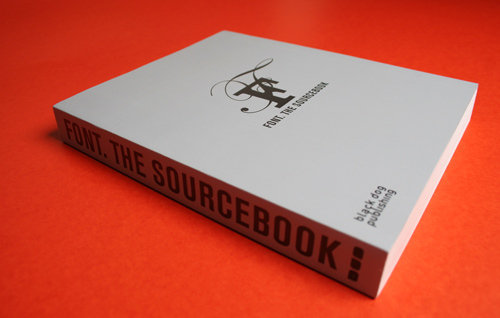
»Font. The Sourcebook« beschäftigt sich mit der Geschichte der Schrift als Kommunikations-, Design-, Darstellungs- und Kunst-Element. So erfährt man ein paar Fakten zu bekannten Schriften oder frischt vorhandenes Wissen einfach auf.
Über 50 Schriften, die die Geschichte am Meisten beeinflusst haben, werden jeweils auf einer Doppelseite behandelt. Darunter die: Akzidenz Grotesk, Baskerville, Caslon, DIN, Frutiger, Garamond, Helvetiva, Interstate, Joanna, Knockout, Lucida, Matrix, News Gothic, Officina, Perpetua, Quadraat, Rockwell, Syntax, Times New Roman, Univers, Walbaum, Zapfina.
Zudem enthalten sind Kommentare und Essays von wichtigen Designern, Kritikern und Typografen unserer Zeit wie beispielsweise David Pearson, Ed Fella, Peter Bil’ak oder Sam Winston.
Das Buch ist eine wertvolle und inspirierende Quelle für jeden Designer und dient sicher auch als Hilfsmittel bei der Auswahl von Schriften.
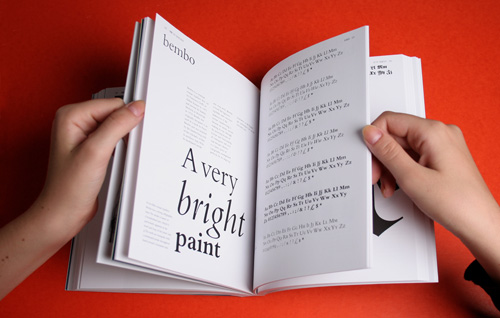
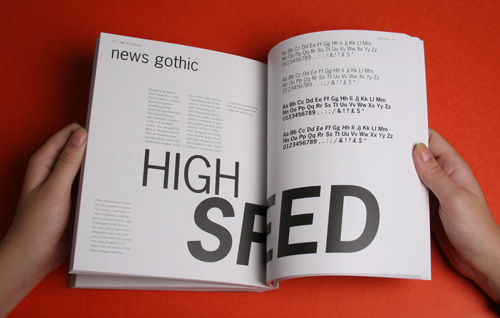
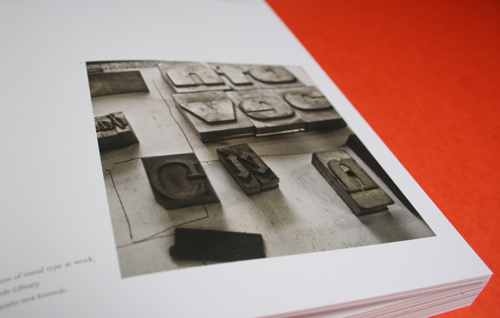
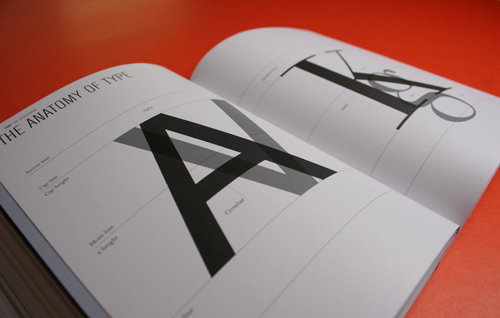
Font. The Sourcebook
Herausgeberin: Nadin Monem
Beitragende: David Pearson, Will Hill, Domenic Lippa, Ed Fella, Teal Triggs, Sam
Winston, Sibylle Hagmann, Peter Bil’ak, and Alexander W. White.
Font. The Sourcebook is an engaging and informative discussion of the history of
typeface as communication, design, display and fine art, combined with an
invaluable and inspirational resource for any designer of the most influential
typefaces throughout history.
Beginning with an accessible and interesting discussion of the emergence and
development of typeface, Font. The Sourcebook looks at the ancient precursors of
modern font in the early scribal forms of pictograms and hieroglyphics, through
wood blocks and the invention of moveable type, the foundry and original type
founders, to the advent of mechanised printing methods and all the way through to
the most innovative work being done in digital typography today.
Font takes up a variety of movements in art and design, exploring the fascinating
stories of the most important typographers in the history of type design, and
explains what makes the most enduring typefaces so significant to the history of the
practice. This lively conversation about the various influences, advances and
theories underlying the history of typography is peppered with celebrity voices
taking up particular debates alive in the field of typography, both historically and
today. Including David Pearson, Will Hill, Domenic Lippa, Ed Fella, Teal Triggs, Sam
Winston, Sibylle Hagmann, Peter Bil’ak, Alexander W. White and Stefan Sagmeister.
Covering the themes of how type is designed and the principles of type, with a
particular look at the impact that changing technologies have on type design, Font
profiles the pioneers, such as John Baskerville, Max Miedinger, Adrian Frutiger,
Herbert Bayer, Claude Garamond, Morris Fuller Benton, Bruce Rogers, amongst
others, before moving on to discuss the designers who are pushing typography
forward today, such as Matthew Carter, Erik Spiekermann, Neville Brody, Peter
Bil’ak, Jonathon Barnbrook and design groups such as Experimental Jetset.
Presenting over 50 of the most important typefaces in history in their full glory, Font. The Sourcebook is an encyclopaedic and inspirational resource for designers and artists. Featuring a short history, an exhaustive library, examples of its most
innovative or inventive applications, these profiles of the most innovative and
important historical and contemporary typefaces currently in use provide a vital
practical tool for graphic designers and typographers to use and be inspired by.
Featured typefaces include Akzidenz Grotesk, Aldus, Avant Garde, Baskerville, Bell
Centennial, Bell Gothic, Bembo, Blur, Bodoni, Caslon, Clarendon, Cooper Black,
Courier, DIN, Fedra, Fette Fraktur, Franklin Gothic, Frutiger, Futura, Garamond,
Gill, Gotham, Helvetica, Interstate, Joanna, Johnston, Knockout, Lucida, Matrix,
Meta, News Gothic, Officina, Optima, Perpetua, Quadraat, Rockwell, Rosewood,
Scala, Stone, Syntax, Thesis, Times New Roman, Trade Gothic, Trajan, Triplex,
Univers, Walbaum, and Zapfino.
With comment from some of the most important designers, critics and
typographers working today, Font. The Sourcebook is a resource no one interested in art and design will want to be without.